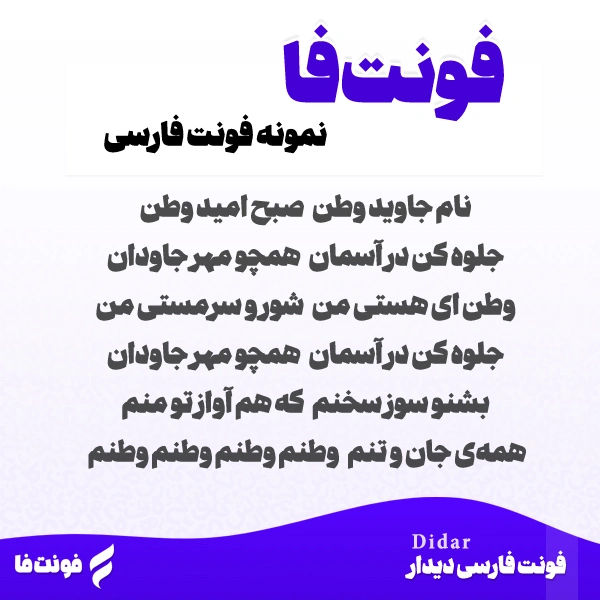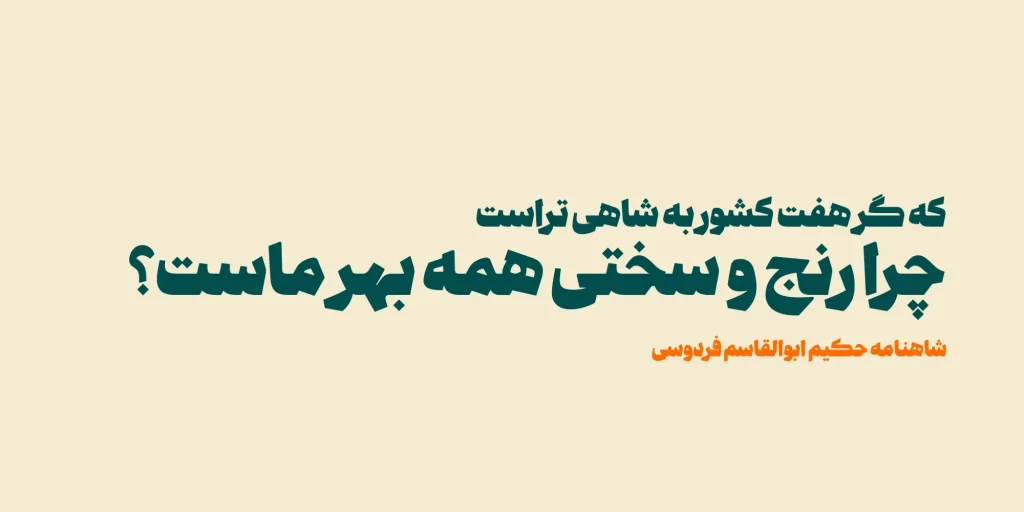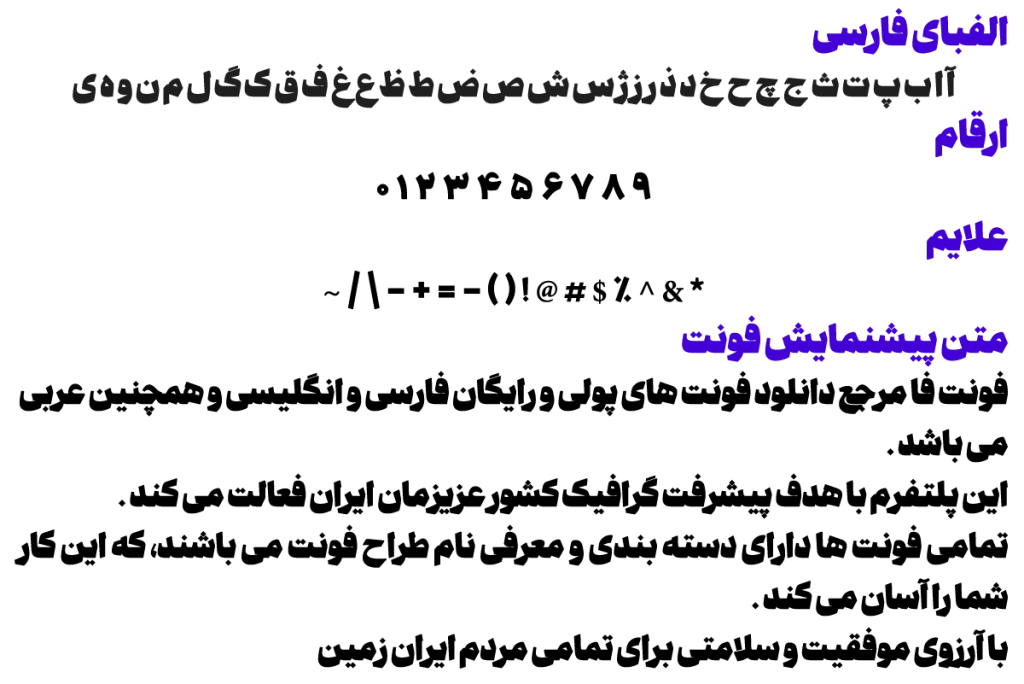
فونت فارسی دیدار - Didar
توضیحات و معرفی فونت دیدار
فونت فوق العاده زیبای معرفی شده توسط رضا بهلول در سال 1404 طراحی و ساخته شده است.
معرفی فونت مربوطه از زبان طراح و سازنده
فونت دیدار با الهام از ظرافت های خط نسخ و ساختاری استوار و منظم طراحی شده است.
این فونت با کرسی پر قدرت و حضور چشمگیر خود در صفحه، انتخابی ممتاز برای تیتر های رسمی و جدی به شمار می آید.
دیدار در نگاه نخست، حس اقتدار و صلابت را منتقل می کند و با دقت در تناسبات و وزن متعادل خود، به نوشته ها اعتبار و اعتماد می بخشد.
طراحی هندسی دقیق و ریتم هماهنگ حروف باعث شده اند این فونت در عین سادگی، جلوه ای باشکوه و حرفه ای به متن ببخشد.
اگر به دنبال فونتی هستید که در تیتر ها با قدرت و وقار ظاهر شود و استواری را به نمایش بگذارد، دیدار گزینه ای بی رقیب است.
همچنین فونت Didar در یک وزن سنگین است.
• Didar Black
در تصویر زیر، شعر کهن «وطنم» با این تایپ‌فیس به نمایش گذاشته شده است.